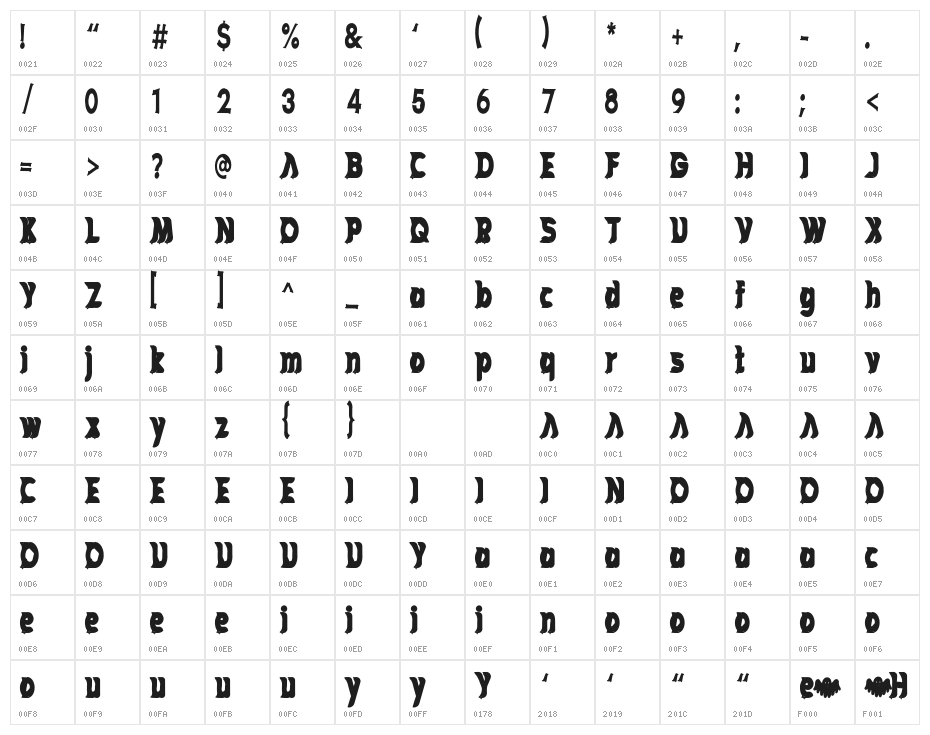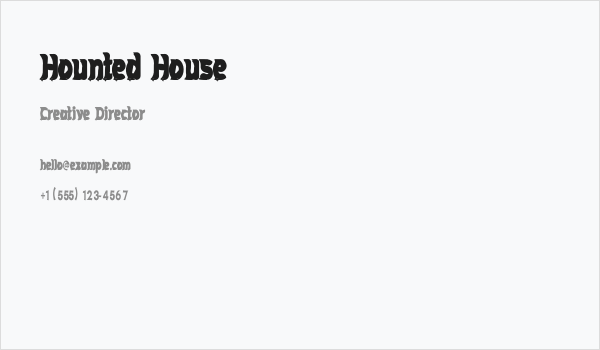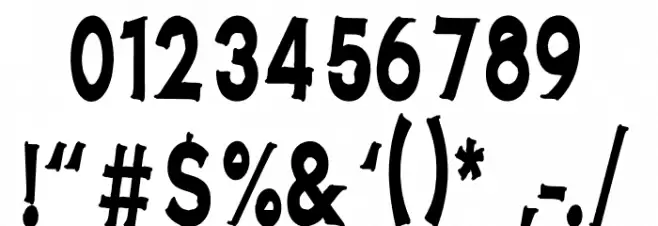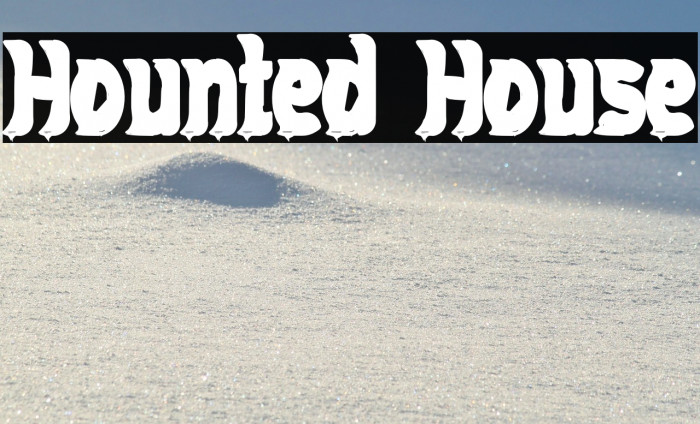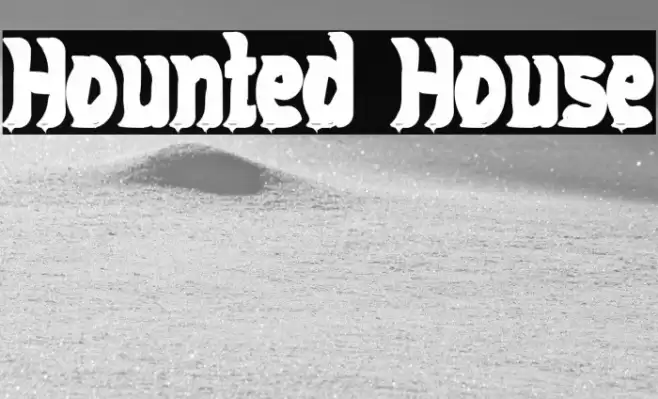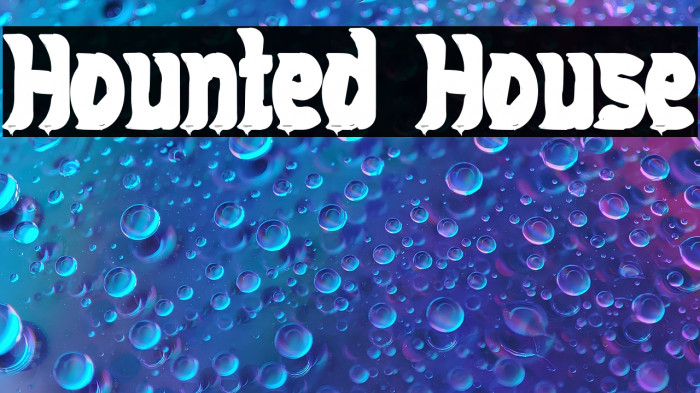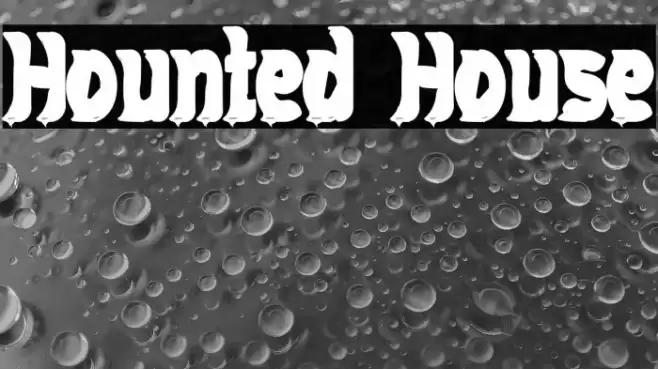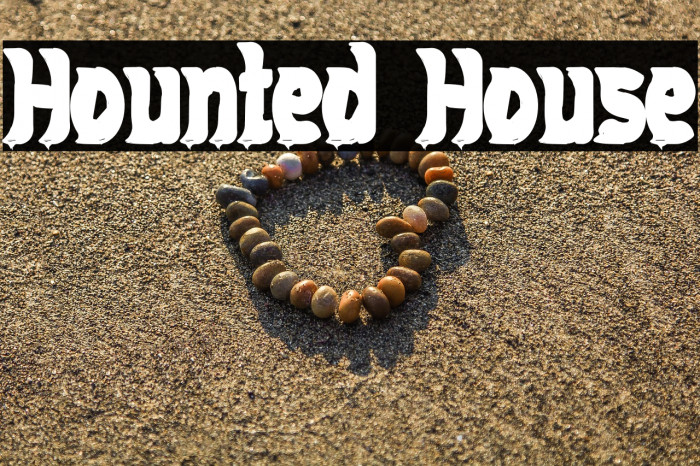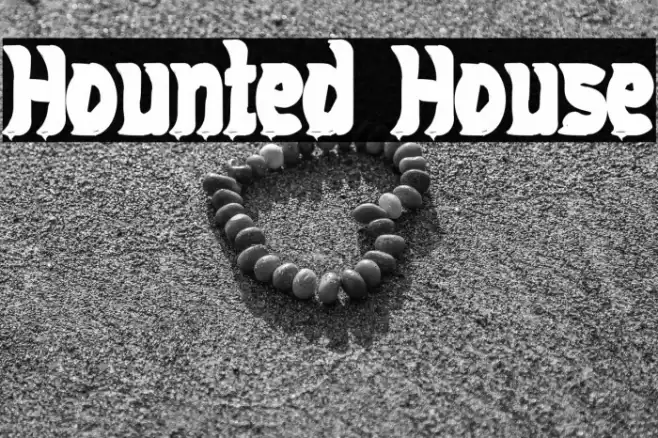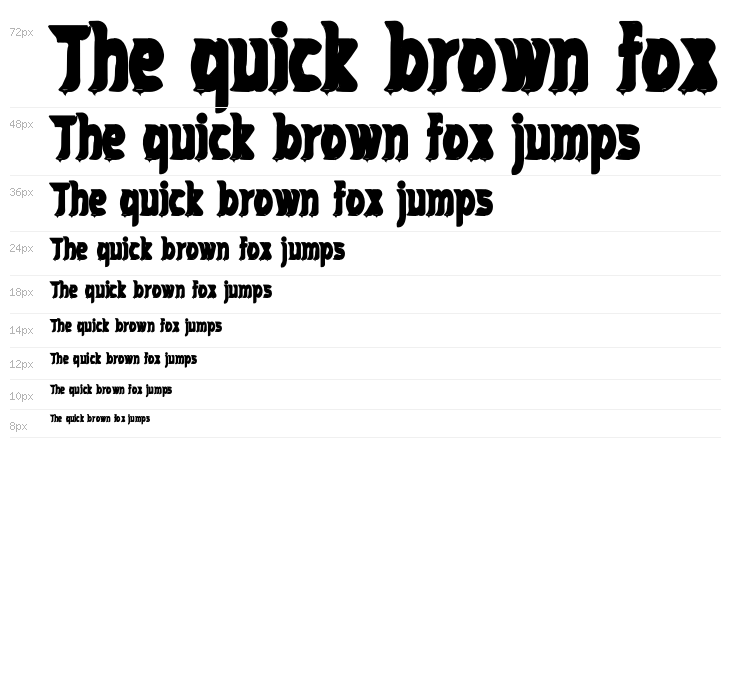
Hounted House Font
| Anwendungsfall | Headlines, Posters, Themed Events |
| Vorgeschlagene Projekte | This font is perfect for Halloween invitations, haunted house posters, spooky event flyers, and themed merchandise. |